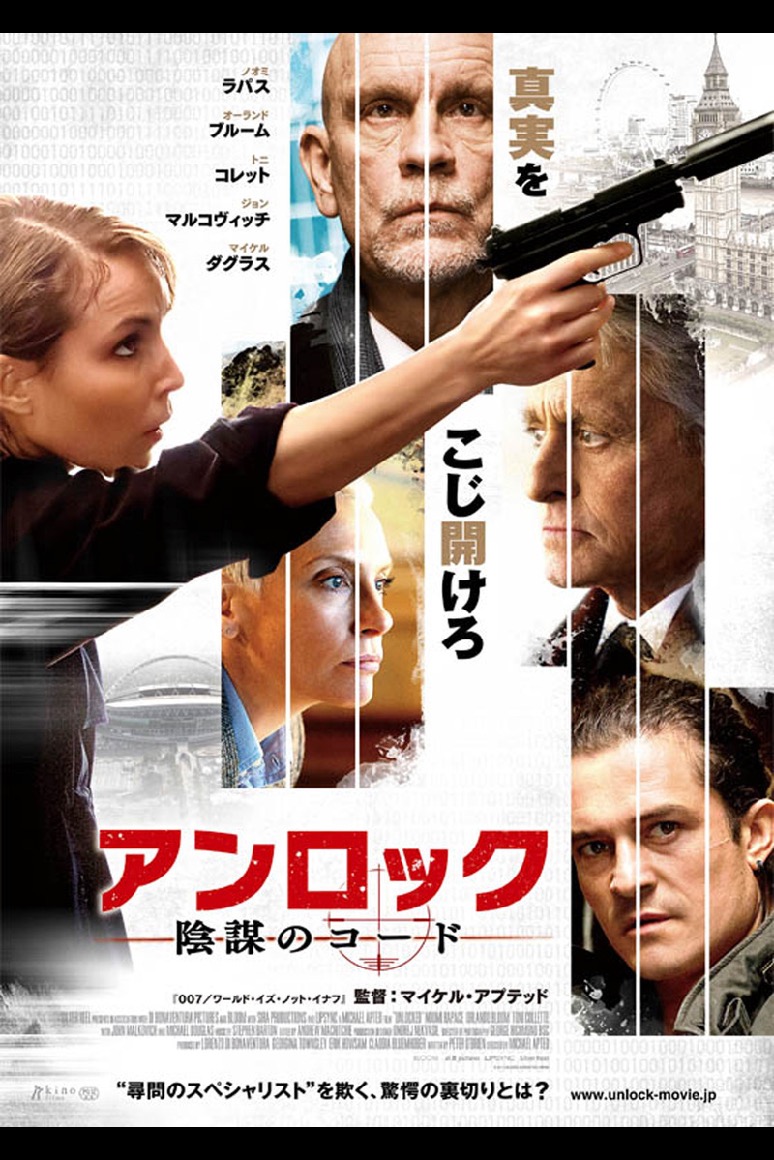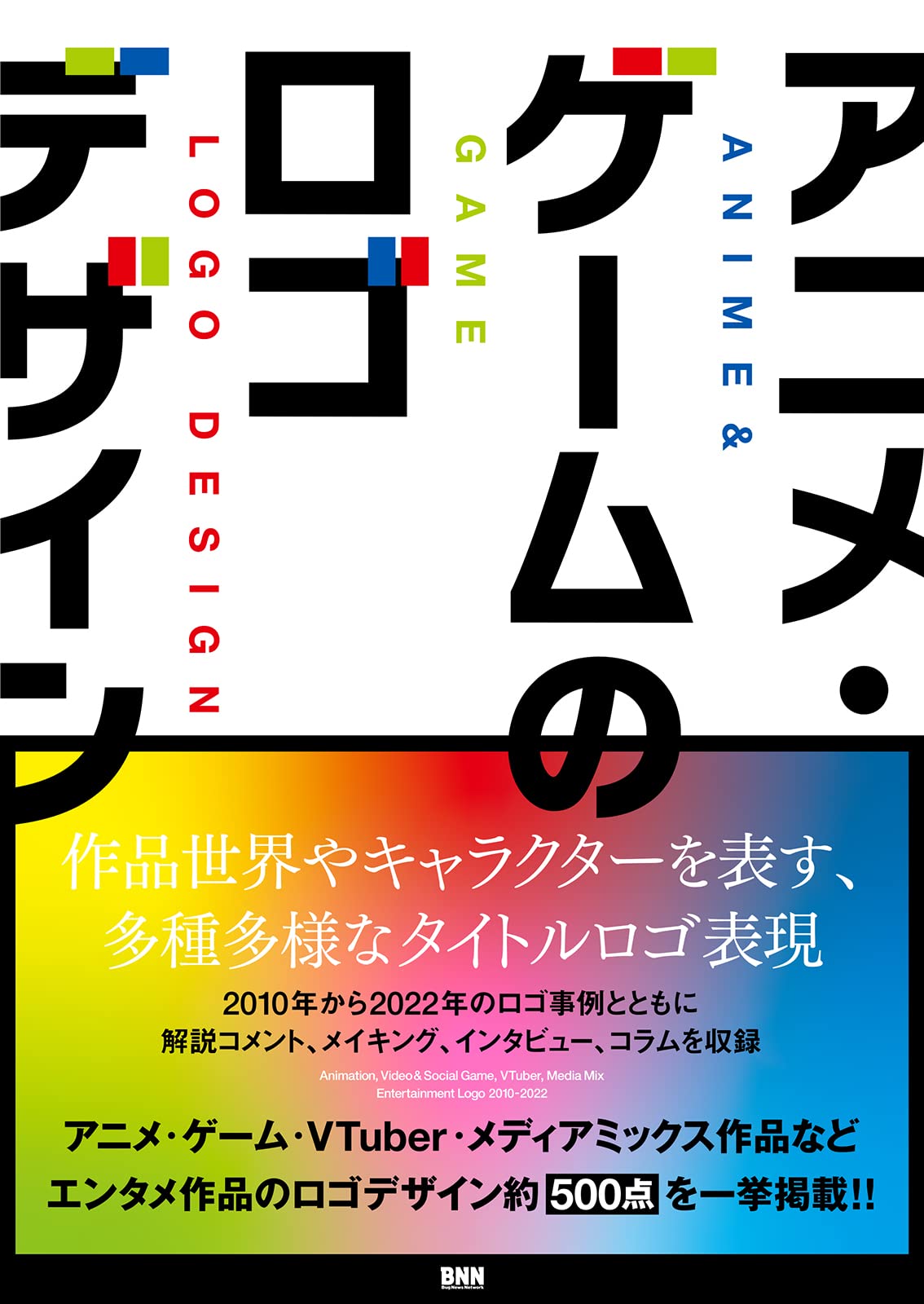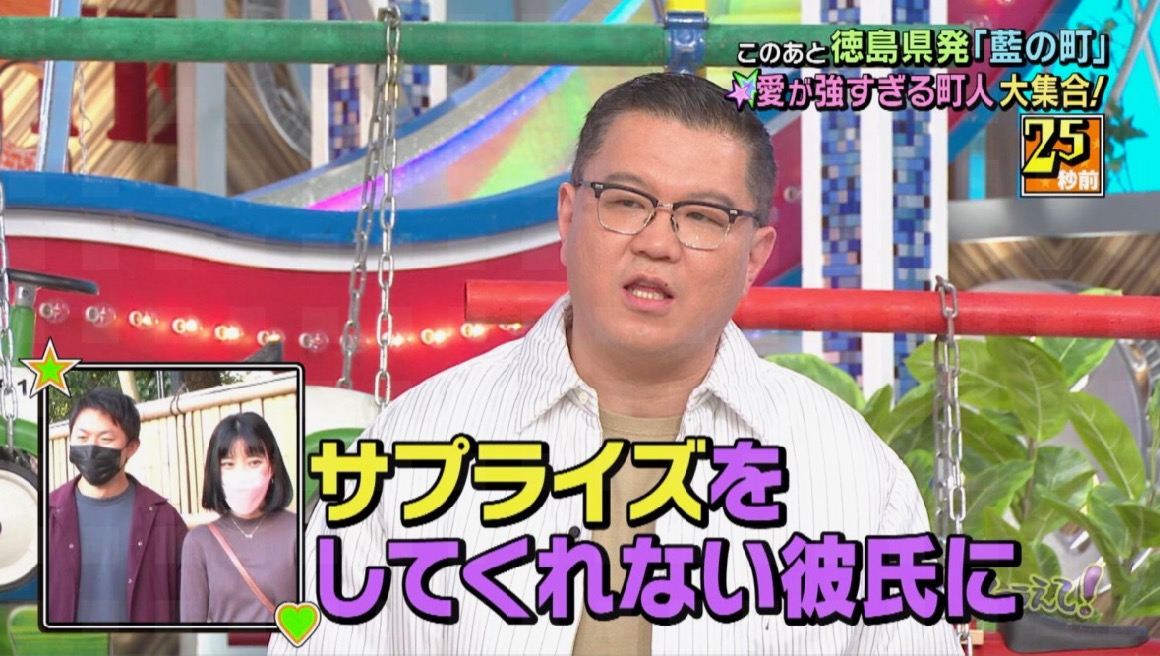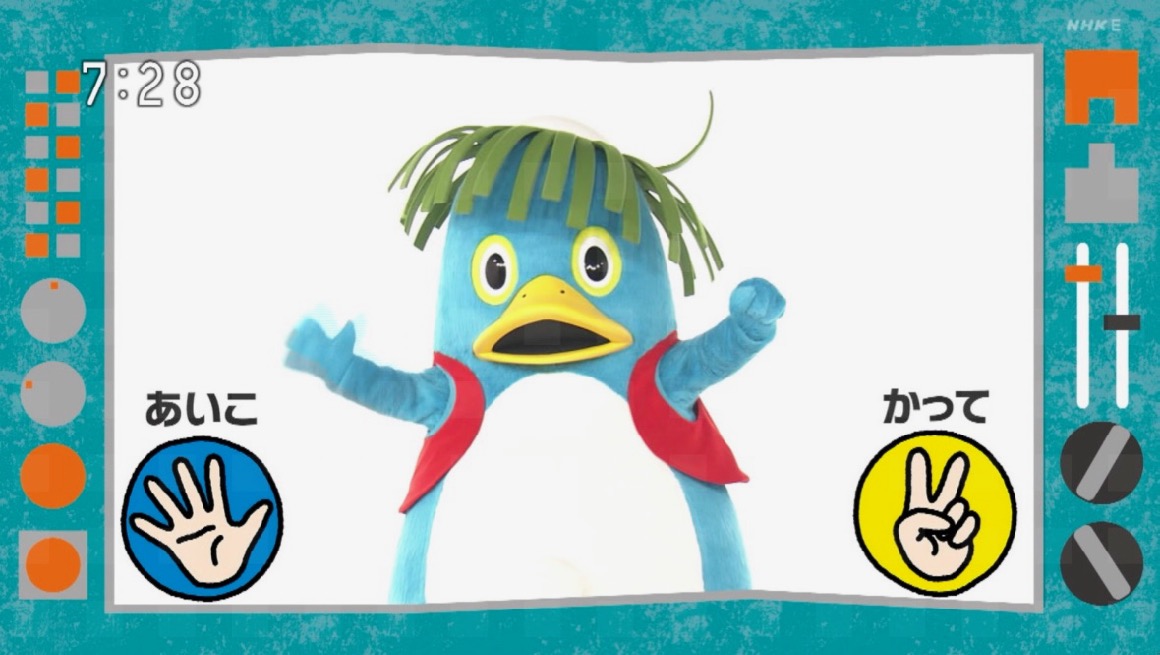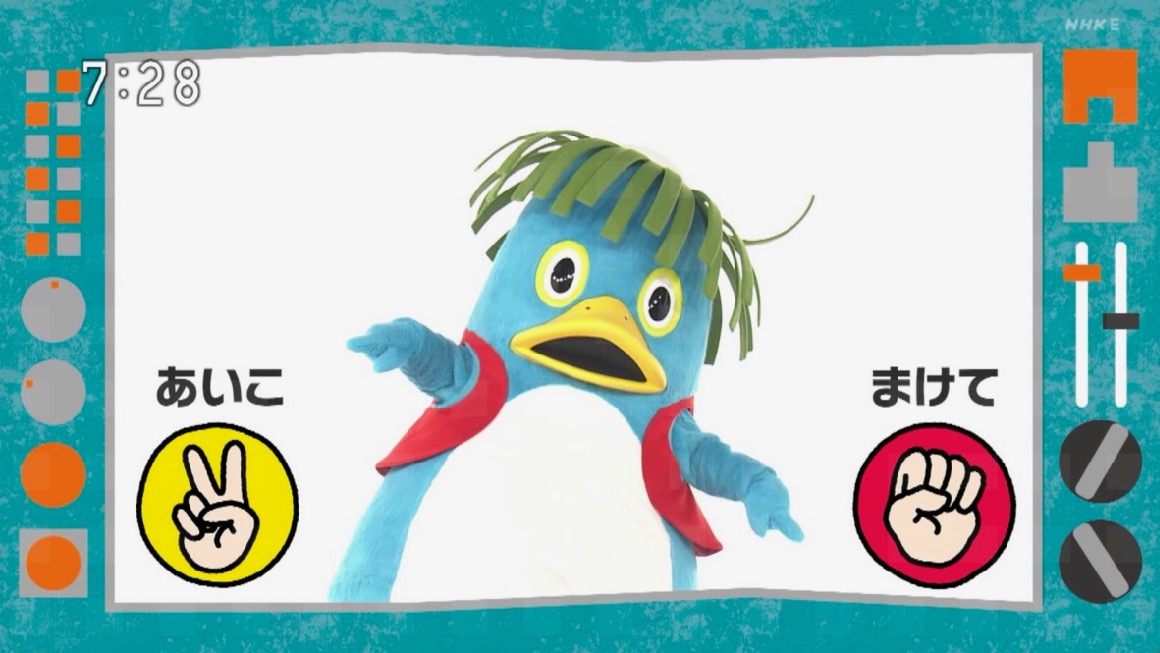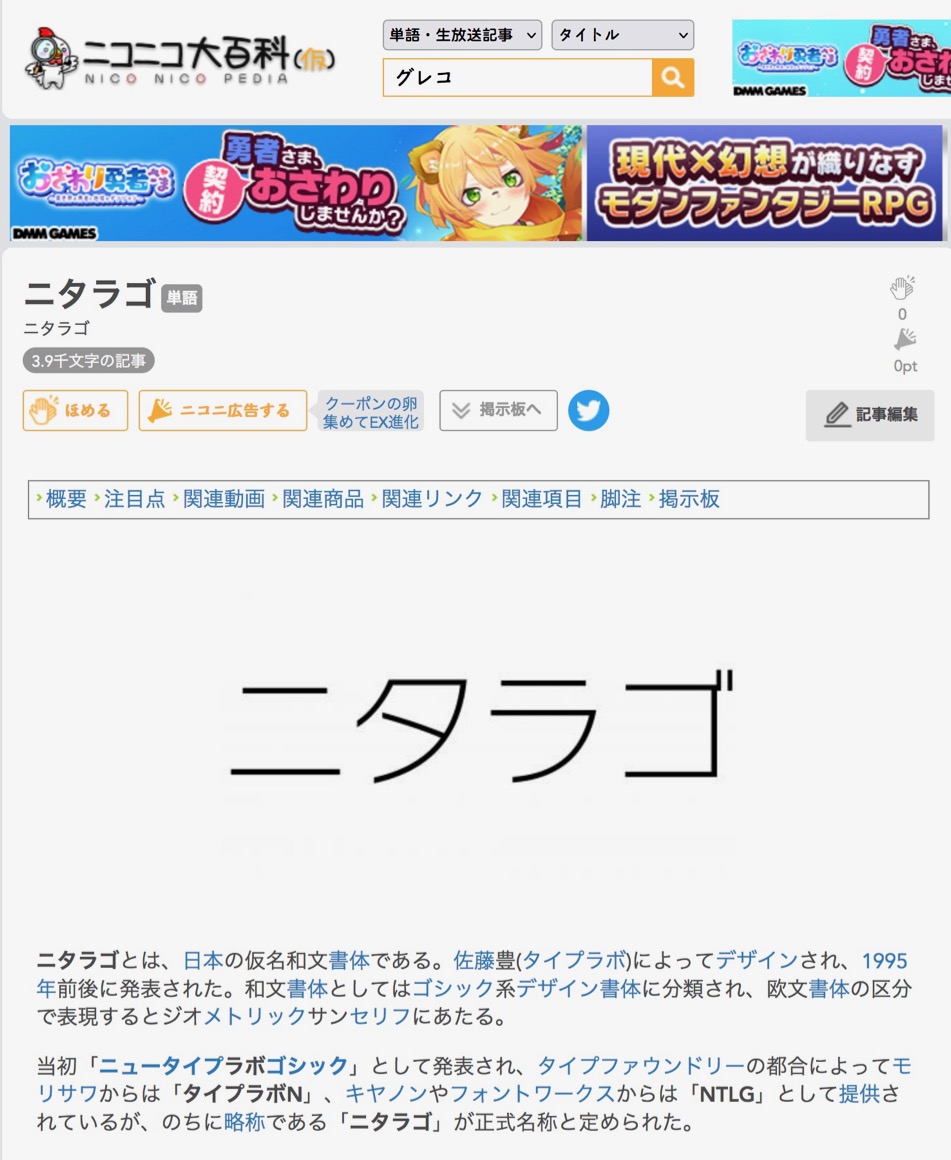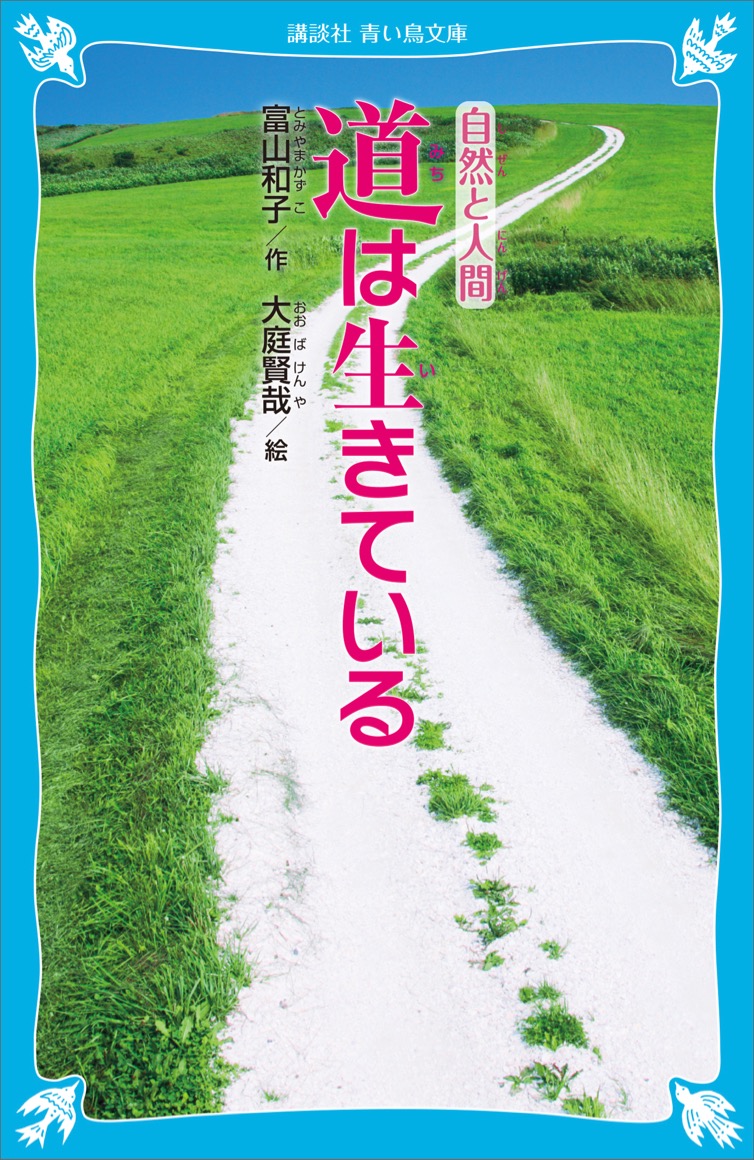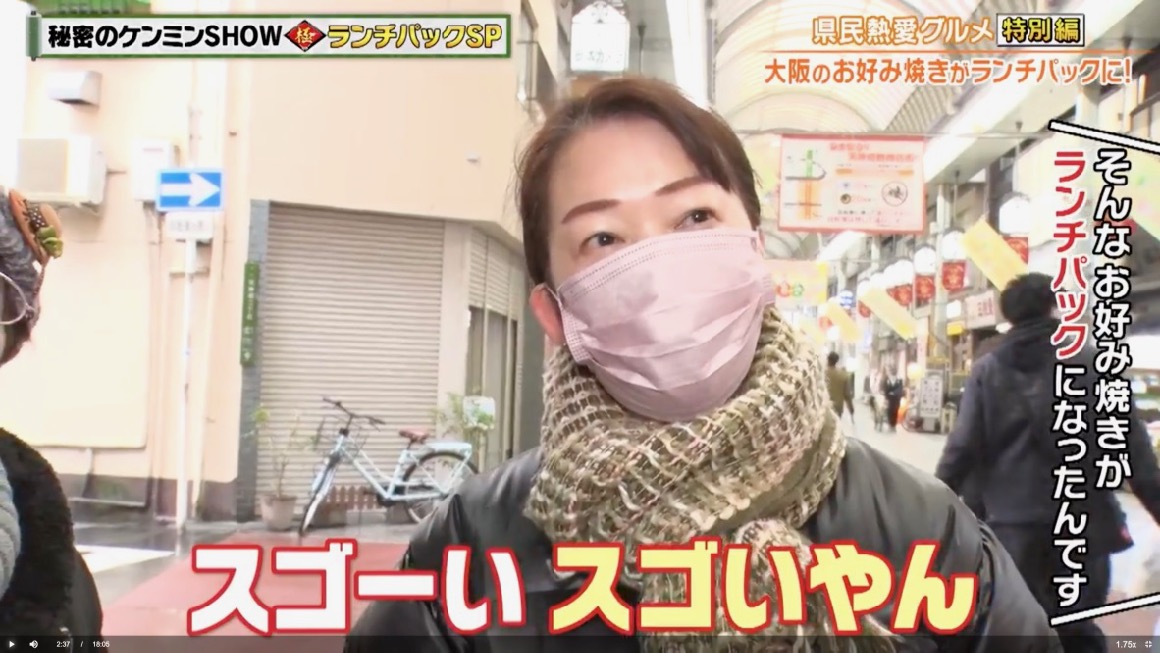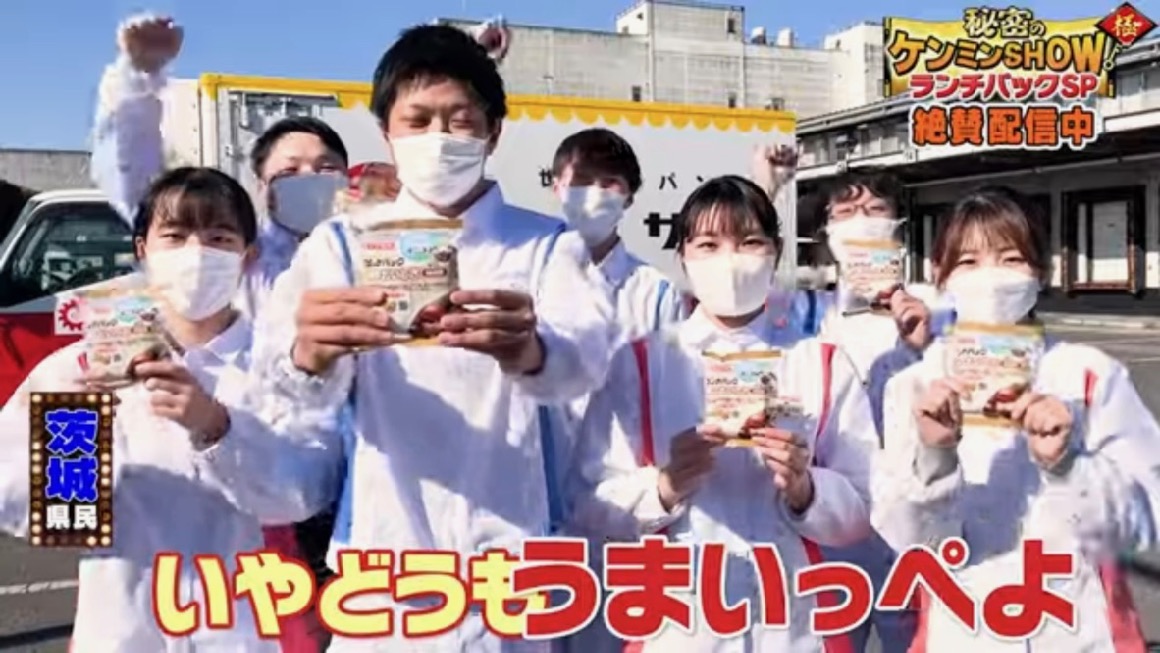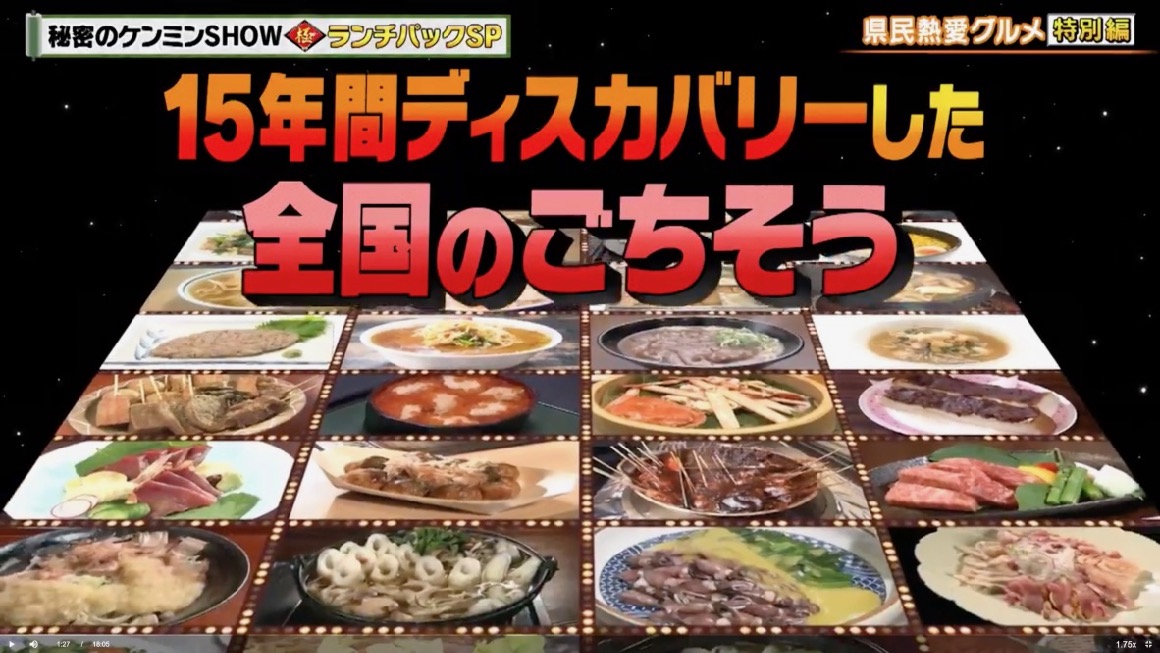
東京保険医協会 takumi
医療機関に貼られている、東京保険医協会発行のポスター。
上部の赤い文字が「ニタラゴルイカ」ですね。
映画のタイトル さとうゆたか
『アクアマン/失われた王国』2024年1月12日(金)全国公開!
これも…。
本の表紙 さとうゆたか
書名:おかあさんはおこりんぼうせいじん
著者:スギヤマカナヨ
発行:PHP研究所
マクドナルドのキャンペーン takumi
Nintendo Switchソフト「ドラゴンクエストモンスターズ3」とマックデリバリーのコラボキャンペーンの特設ページ。
マクドナルドではニタラゴがすっかり制定書体になっているようですが、こんなキャンペーンの告知でも使われているんですね。
最後にこれも。
広告画像 さとうゆたか
subway
まだある。
広告画像 さとうゆたか
楽天ペイアプリ。
テレビ番組 さとうゆたか
日本テレビ「笑ってコラえて!」。
法律事務所のCM takumi
平松剛法律事務所のCMでF社のニタラゴが使われています。
広告画像 さとうゆたか
日テレの番組 takumi
日テレで放送されている「キントレ」という番組より。
ニタラゴ書体が使われています。
これも…。